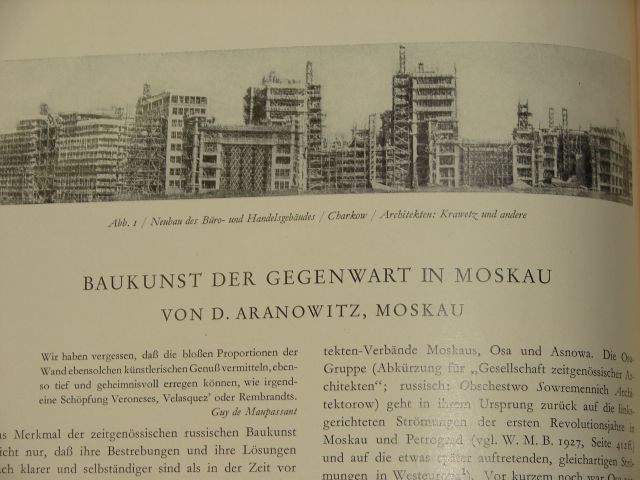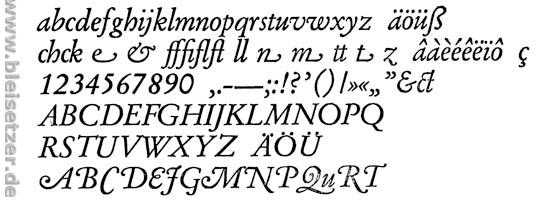
Wasmuths Monatshefte für Baukunst
Kann mir jemand sagen, welche Schriften hier verwendet wurden?
Ich finde leider auf die Schnelle kein anderes Bild:
Schau mal, ob das ß links in kurz vor Beginn der Oberlänge einen kleinen Querstrich nach links hat. Steht im Fließtext.
Ich denke:
Gruppe II - Französische Renaissance-Antiqua - Garamond (Stempel)
D.Stempel AG, Frankfurt am Main
Erstguß 1925
Rudolf Wolf
Intern immer als "Hausschrift" bezeichnet, möchte ich dennoch den Namen des Entwerfers nennen, der diese Schrift geschaffen hat.
Gibt es denn ein elektronisches Equvalent?
...aber die Zahlen sind Mediävaziffern, oder?
Ist das bei einem traditionellen Satzverfahren vorgegeben oder wird das erst beim Setzen so gesetzt?
Superschön, die schönste Garamond meiner Meinung nach.
hmm, was mich jetzt wundert, ist das geschwungene Italic-z nur beim SSC Italic Schnitt mit dabei, oder in einem Expert-Schnitt? Ich frage, weil ich beide nicht besitze…
Im Italic-Schnitt stellt sich das "z" so dar -
Edit:
Okay, das italic swash-z ist ein "alternate", somit ist die Frage beantwortet.
...aber die Zahlen sind Mediävaziffern, oder?
Ist das bei einem traditionellen Satzverfahren vorgegeben oder wird das erst beim Setzen so gesetzt?
Ich verstehe die Formulierung "bei einem traditionellen Satzverfahren" nicht.
Diese Schriften wurden Mitte der 20er Jahre entworfen. Im Falle der Garamond nach erhaltenen Originalen des Meister Garamond aus dem 16. Jahrhundert. Und da gehörten diese Mediaeval-Ziffern dazu. Wie Du selbst im Fließtext sehen kannst, sind sie sehr gut lesbar.
Ah, jetzt verstehe ich Deine Frage - Entschuldigung.
Nein, die werden nicht beim Setzen so gesetzt.
Die sind so.
Aber die tu'n auch nix. Die woll'n nur spielen :)
Wenn ich diese Seite "nachbauen" wollte, welche Schnitte bräuchte ich:
- Stempel Garamond Roman
- Stempel Garamond Italic
Was bedeutet "Stempel Garamond Roman OsF"?
>Wenn ich diese Seite "nachbauen" wollte, welche Schnitte bräuchte ich
- Stempel Garamond™ Pro Roman (Opentype)
- Stempel Garamond™ Pro Italic (Opentype)
Aber sind die "alternates", also die Swash-Buchstaben, in der Pro Version mit dabei, oder nicht? Anhand der Icons ja nicht, oder sehe ich das nicht richtig...